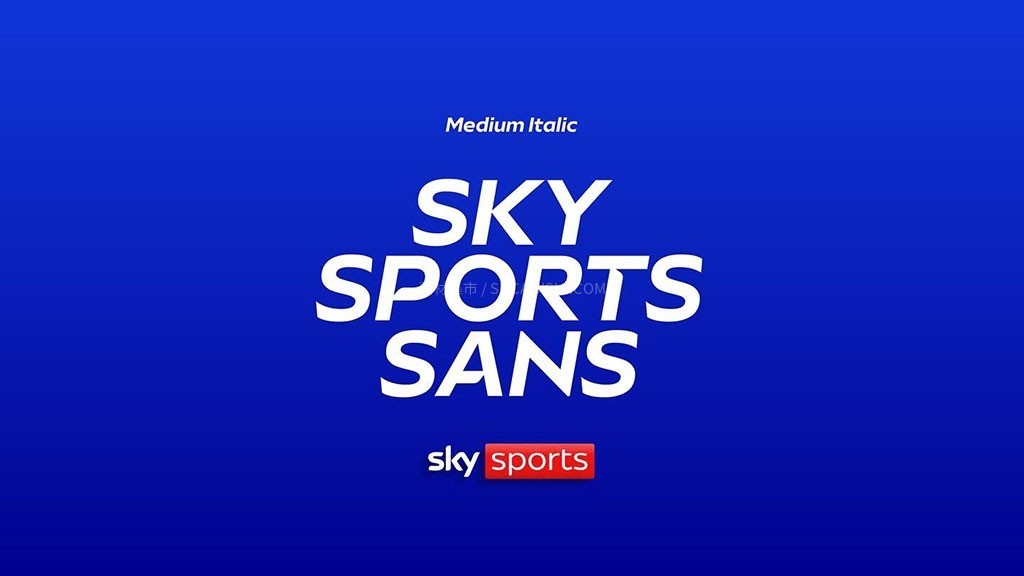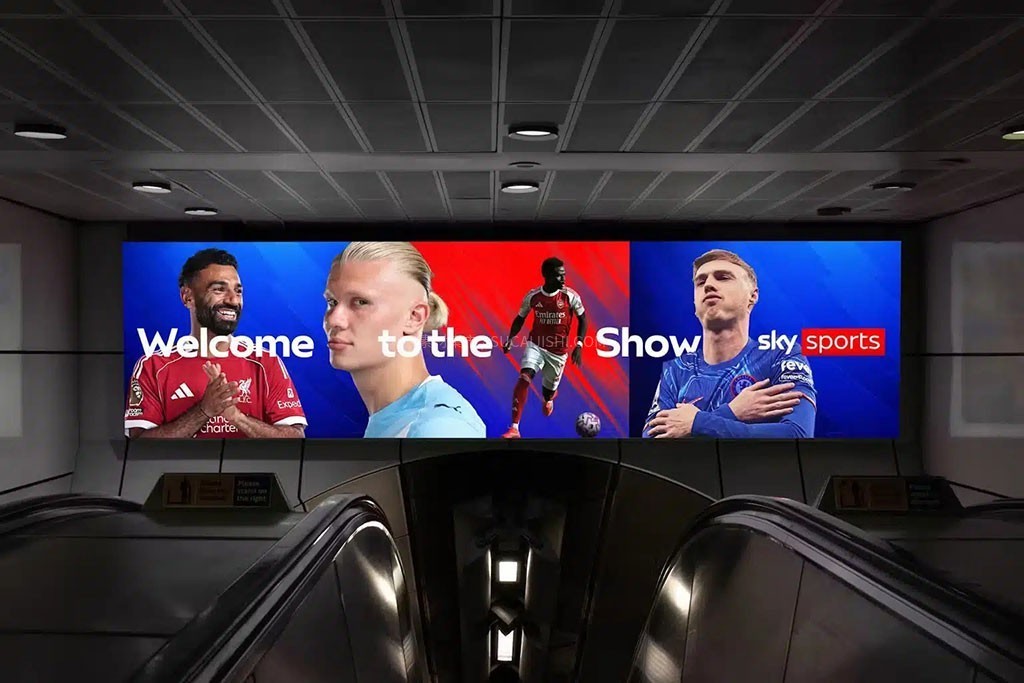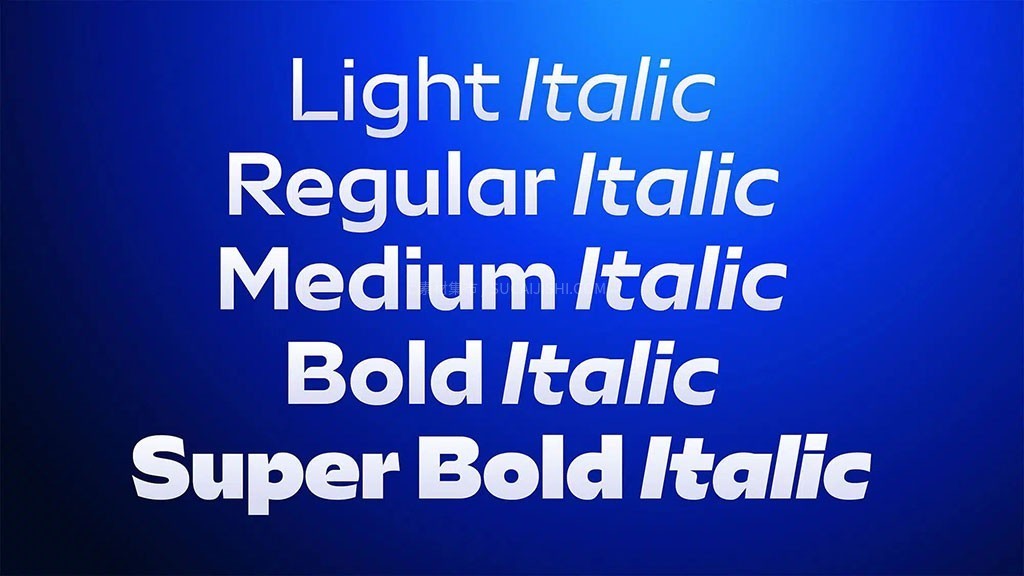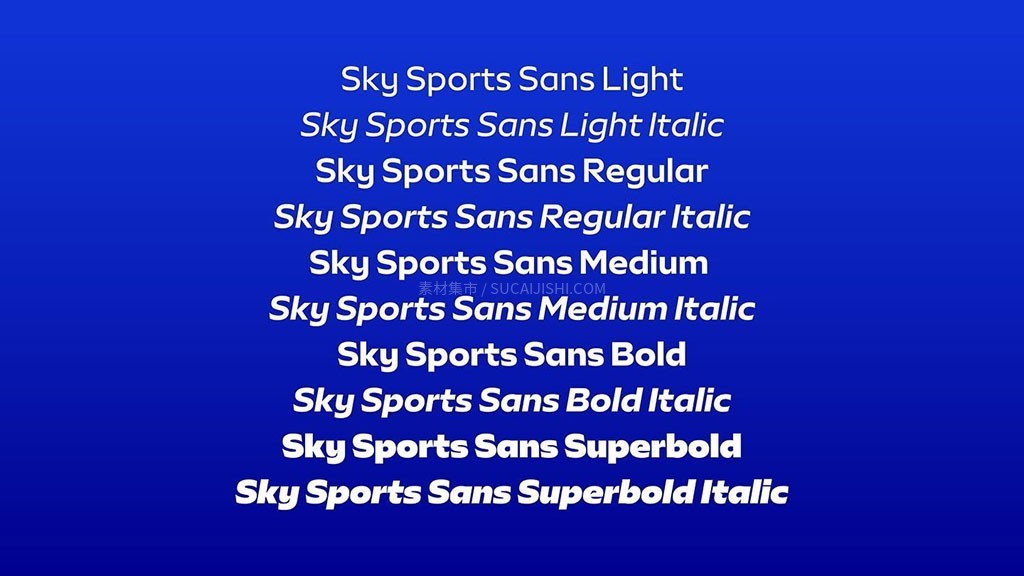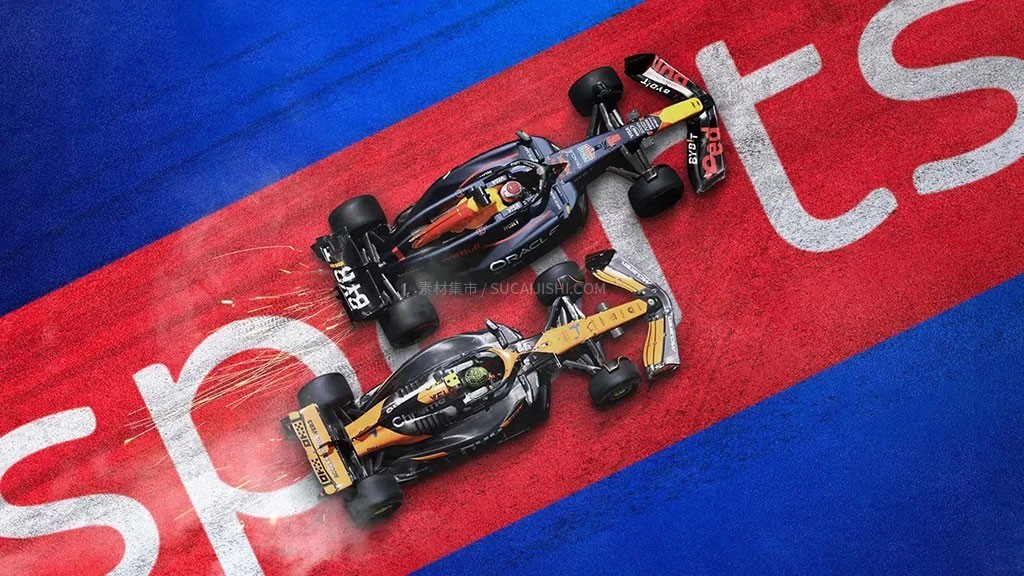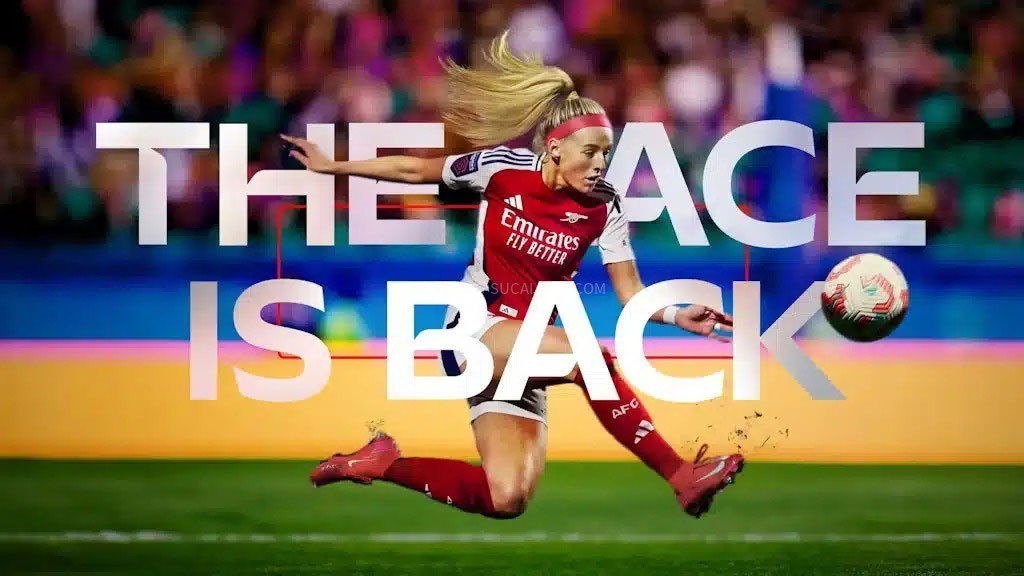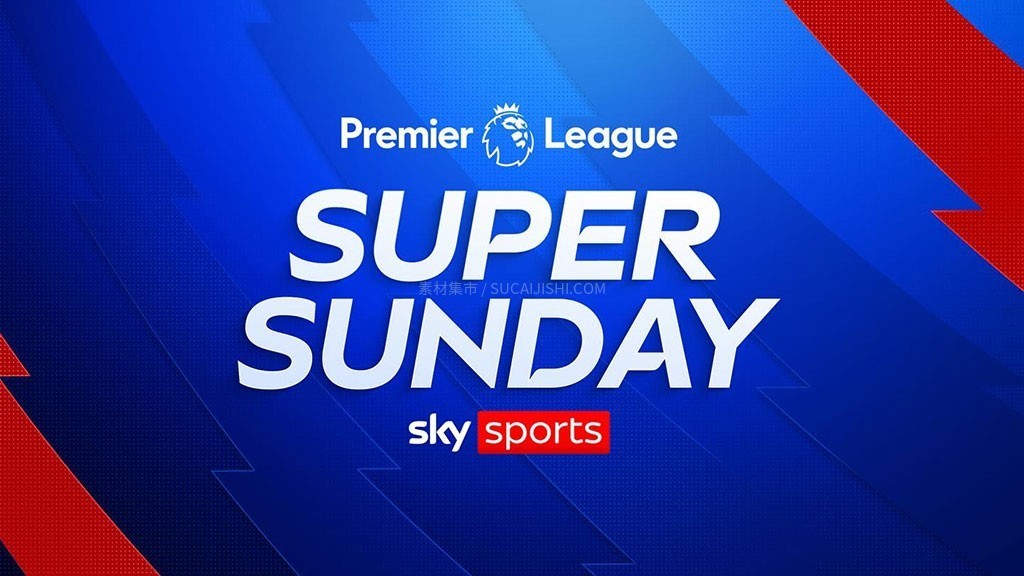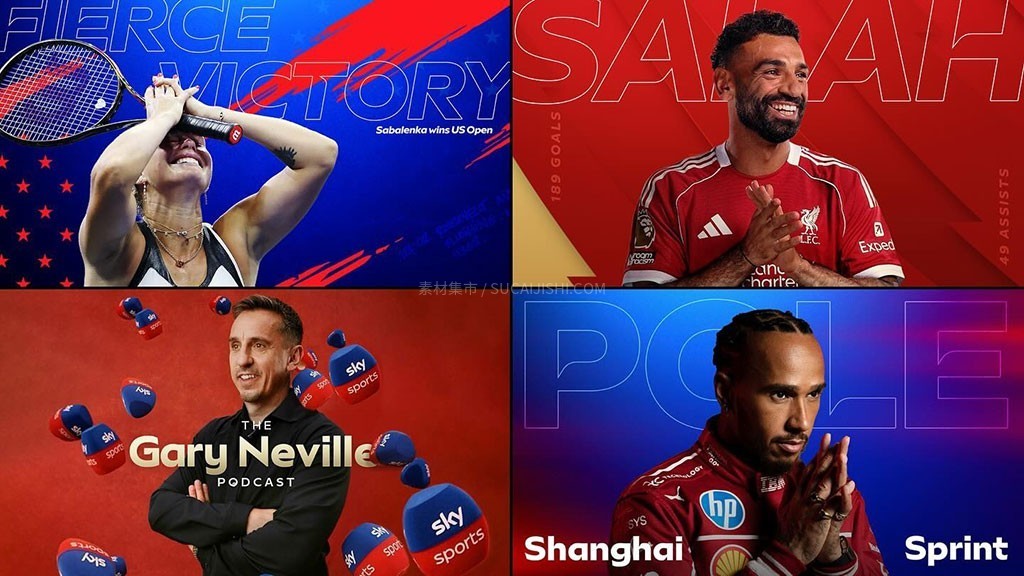
Sky Sports Sans 体育品牌定制英文字体
Sky Sports Sans 是由知名字体工作室 F37® 为全球顶级体育转播商天空体育(Sky Sports)量身打造的全新专属定制字体系列。该字体旨在统一旗下众多子品牌(足球、F1、板球等)的视觉形象,在保持体育新闻权威性的同时,注入了热情、友好与创新的品牌基因。字体设计兼具个性与极高的精准度,拥有出色的灵活性,能够完美胜任从极具视觉冲击力的醒目标题到密集的赛事统计表格等各种复杂排版需求,是提升品牌一致性与专业氛围的绝佳选择。